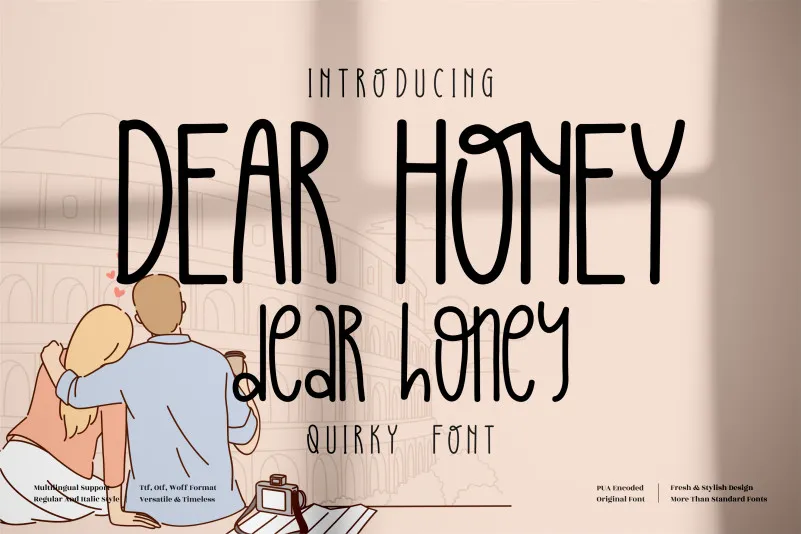
DEAR HONEY Font – Fonte Grátis
DEAR HONEY Font
A font ‘DEAR HONEY’ é uma opção ideal para projetos que pedem uma pitada de irreverência e criatividade. Ela vem em formato de escrita manuscrita, com traços curtos e irregularmente distribuídos que garantem um toque único e memorável. Esta font é perfeita para qualquer projeto que precise se destacar, seja ele como logomarcas ou designs de marcas, embalagens de produtos, capas de livros, identidades digitais, cartões de nome, convites, cartazes, etiquetas, imagens fotográficas, marca d’água, eventos especiais e muito mais. Com sua personalidade descompromissada e uma presença única, ela certamente irá enriquecer seu design com um toque especial e divertido. O designer perspectype criou esta font para aqueles que apreciam o brilho da originalidade em seus projetos.